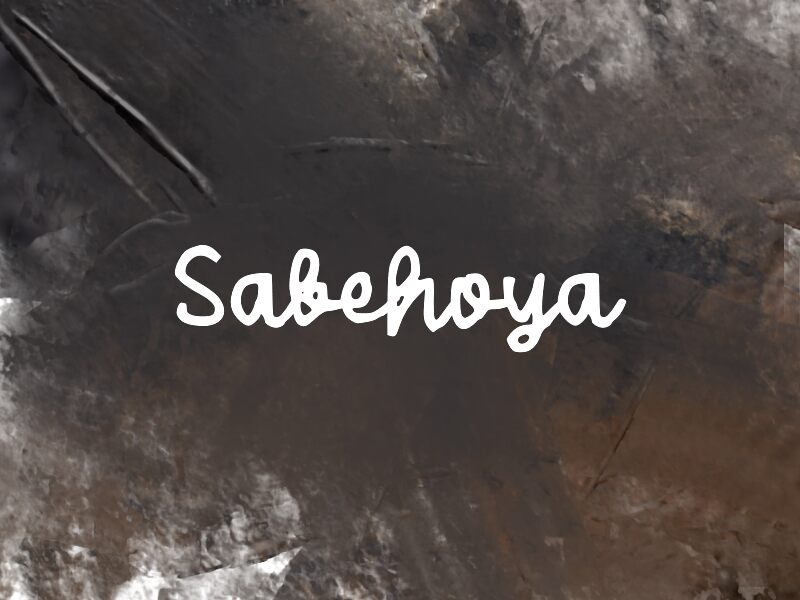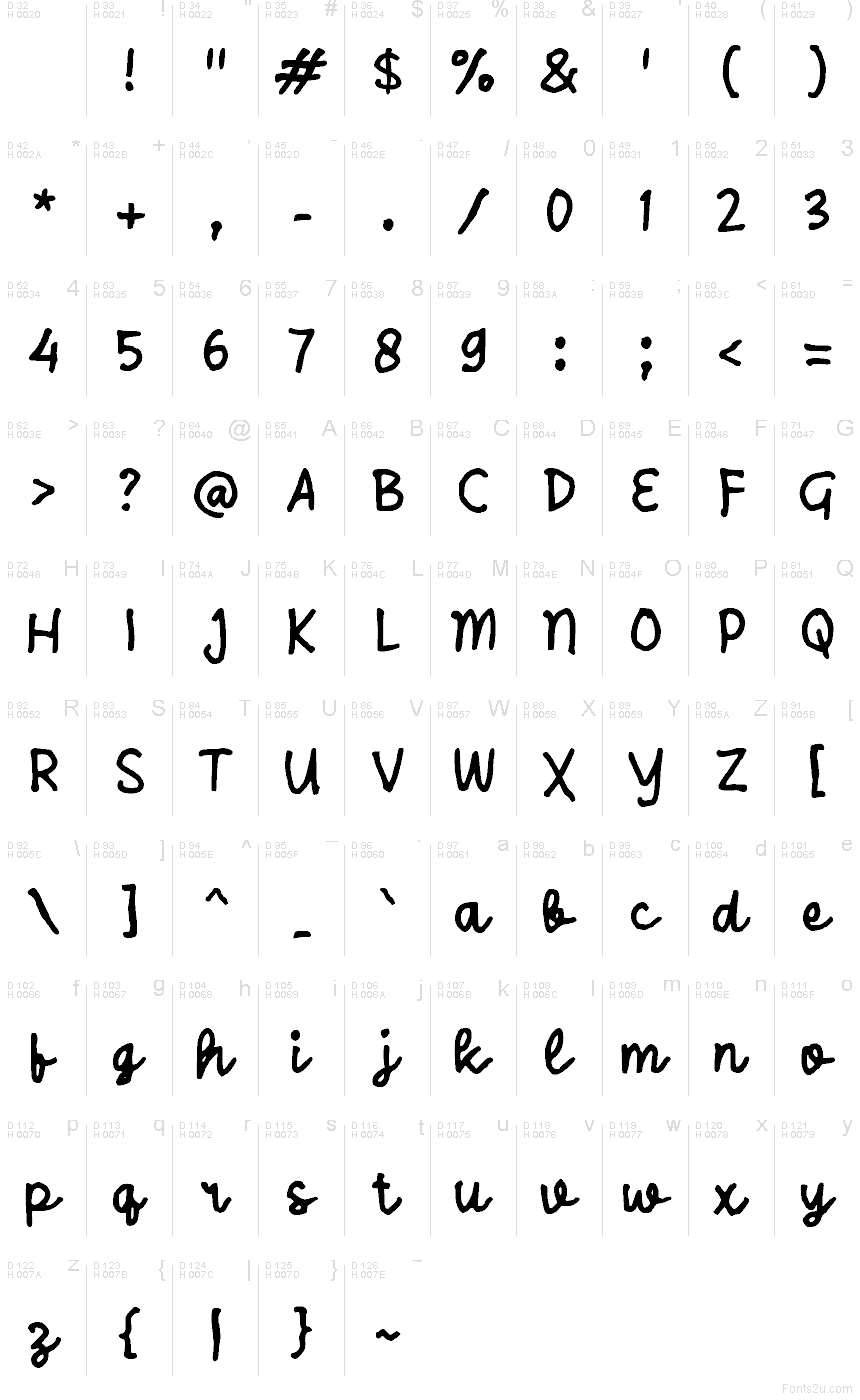
Sabehoya
Sabehoya 由 Wep 设计,是一款免费的手写字体,其轮廓呈现出宽广且流畅的韵律,带有类似马克笔书写的随意感。字体线条圆润柔和,但其长水平连接和偶尔出现的细长圆圈,使其摆脱了随性或平庸的刻板印象。
这种组合使简短的名称和标题在咖啡馆品牌设计、产品标签、社交媒体帖子、贺卡及简约包装中表现出色。它同样适用于引文图形和徽标草图,其中舒展的连接和轻松的笔触足以支撑整个布局,无需额外装饰。